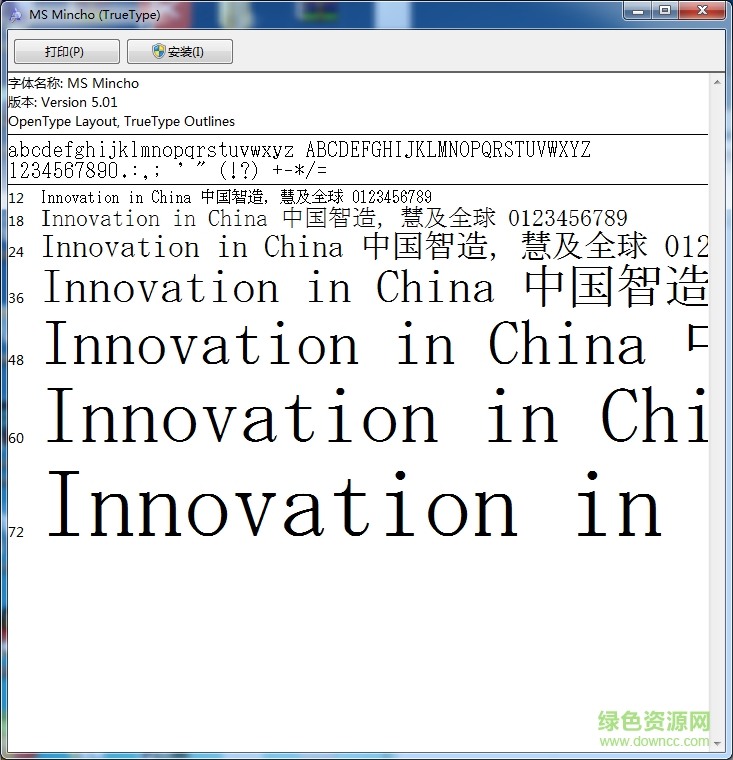
msmincho.ttc字體
ms mincho字體是一款非常時(shí)尚好用的英文字體,支持漢子、英文、數(shù)字等多種方式輸入顯示,使用簡(jiǎn)單極具個(gè)性??靵?lái)綠色資源網(wǎng)下載體驗(yàn)吧!
ms mincho字體字體介紹
ms mincho字體是一款風(fēng)格較獨(dú)到的字體,線條簡(jiǎn)潔,筆畫(huà)規(guī)范,略帶像素風(fēng)格,效果引人注目,該字體常常見(jiàn)于電腦系統(tǒng)中。